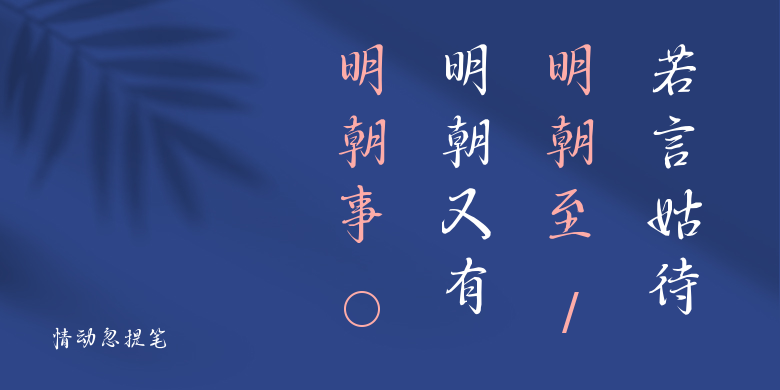
情动忽提笔
情动忽提笔,这款字体结构工整、笔画清晰,兼顾美观与易读性,适用于标题、正文、海报、包装、LOGO 等多种场景。字形优雅稳定,风格百搭耐看,适配日常排版与创意设计,让文字呈现更舒适、更具质感。情动忽提笔一笔一画,皆是细节,以均衡的比例、流畅的线条打造舒适视觉体验,字形端正大气,风格简约现代。无论是商业设计、品牌宣传还是日常排版,都能轻松驾驭,让文字更有格调与力量。情动忽提笔字体下载。